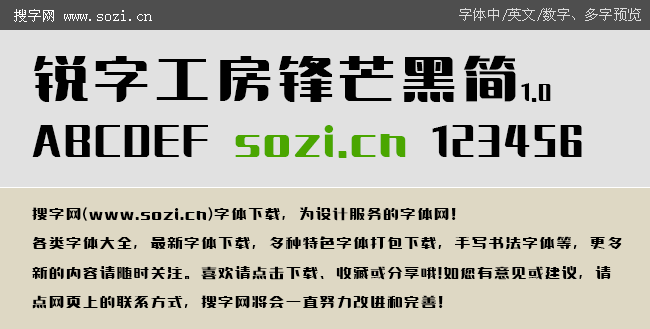
銳字工房鋒芒黑簡(jiǎn)
搜字網(wǎng)提供一款非常藝術(shù)的黑體銳字工房鋒芒黑簡(jiǎn)下載,銳字工房鋒芒黑簡(jiǎn)是一款字形方正的銳字工房字體,該字體極具藝術(shù)感,簡(jiǎn)潔大方,適用于包裝印刷、廣告設(shè)計(jì)、平面設(shè)計(jì)、書(shū)籍報(bào)紙等領(lǐng)域。